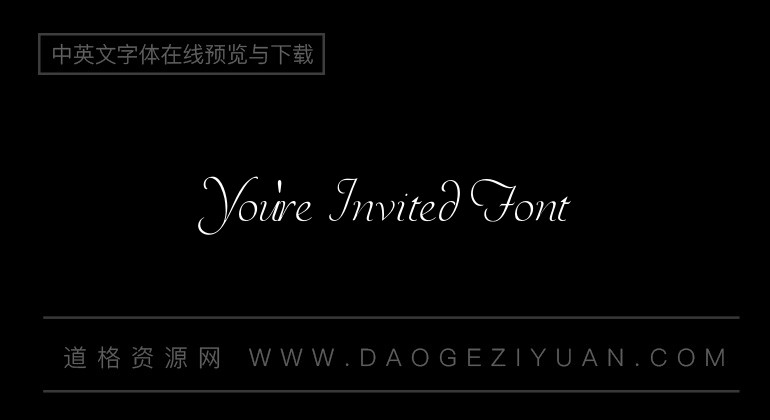
You're Invited Font
You're Invited Font(你受邀字体)是一种手写风格的字体,适用于各种场合的卡片、邀请函、海报等设计中。这种字体的特点是有着非常连贯的曲线和波浪线,使得文本看起来非常有趣和充满活力。 You're Invited Font 具有多种字形,包括大写字母、小写字母、数字和标点符号。这些字形在大小和粗细方面也有所不同,可以满足不同设计需求的使用。 总之,You're Invited Font 是一种非常适合用于庆祝和欢乐气氛的字体,可以增添你设计作品的个性和魅力。
You're Invited Font是一款非常不错的手写艺术字体,具有很好的视觉感,适合于文化类的宣传设计、商业类品牌的广告和产品包装设计以及个性化文字排版等较多场景。